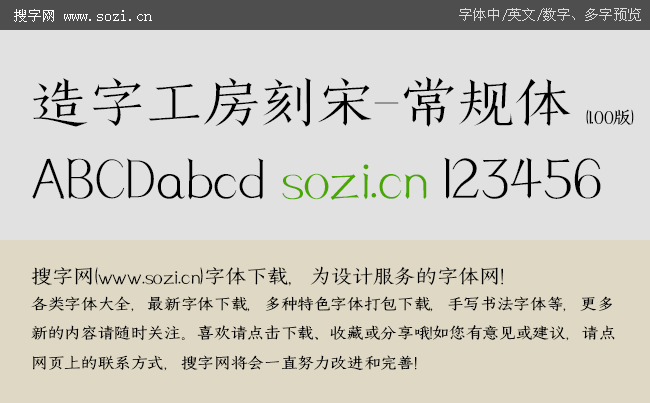
造字工房刻宋常規(guī)體
搜字網(wǎng)給大家提供一款很精致的造字工房刻宋常規(guī)體字體下載。造字工房刻宋體秉承古籍木版印刷之字形特性,筆畫具刀刃之鋒美,且造型秀美適意、剛?cè)岵?jì),且具有極強(qiáng)的時(shí)尚感。蘊(yùn)傳統(tǒng)宋體風(fēng)格特性,在傳統(tǒng)筆形間創(chuàng)新,結(jié)合當(dāng)代設(shè)計(jì)視覺(jué)環(huán)境,此款字體易讀性更強(qiáng),適用于適用于包裝、畫冊(cè)、書籍排版等視覺(jué)環(huán)境,有著極強(qiáng)的應(yīng)用空間。